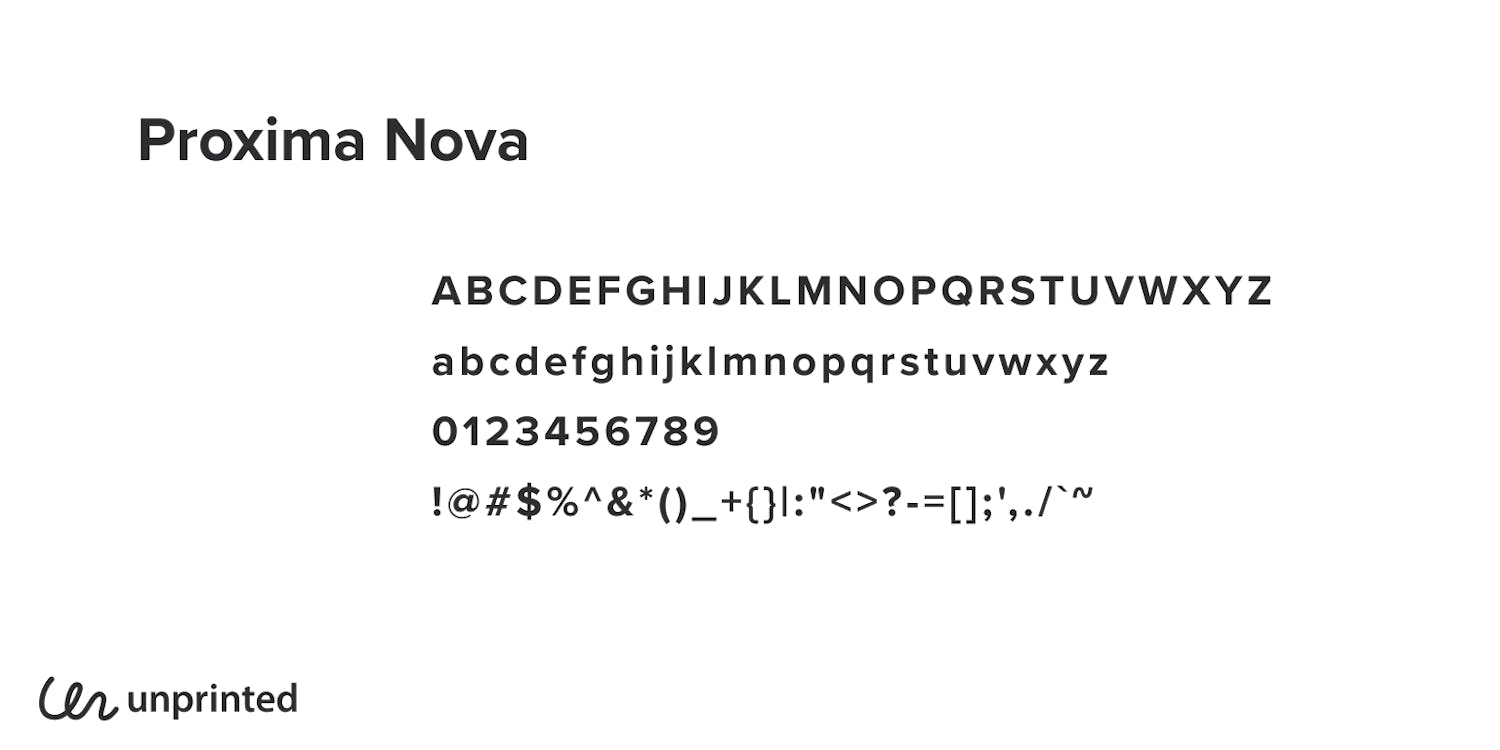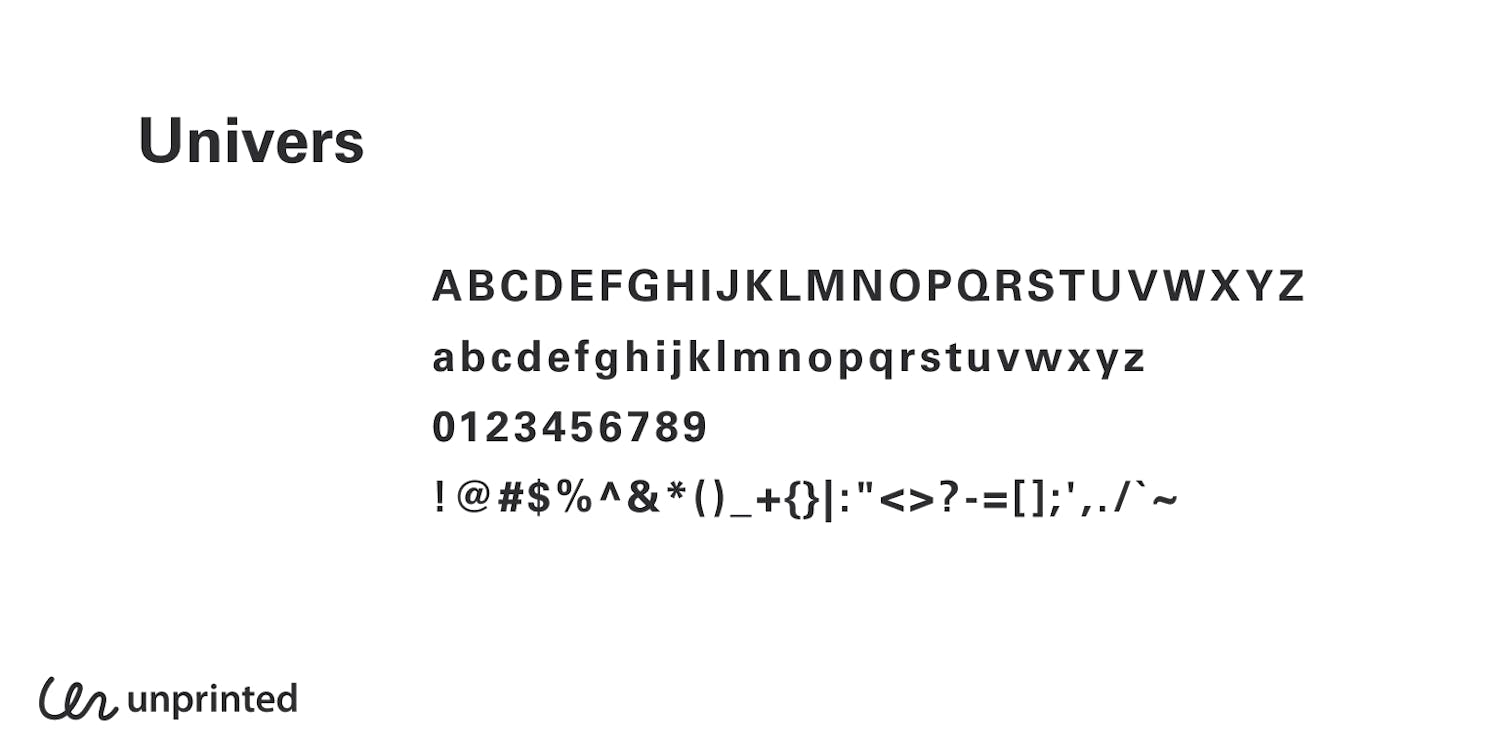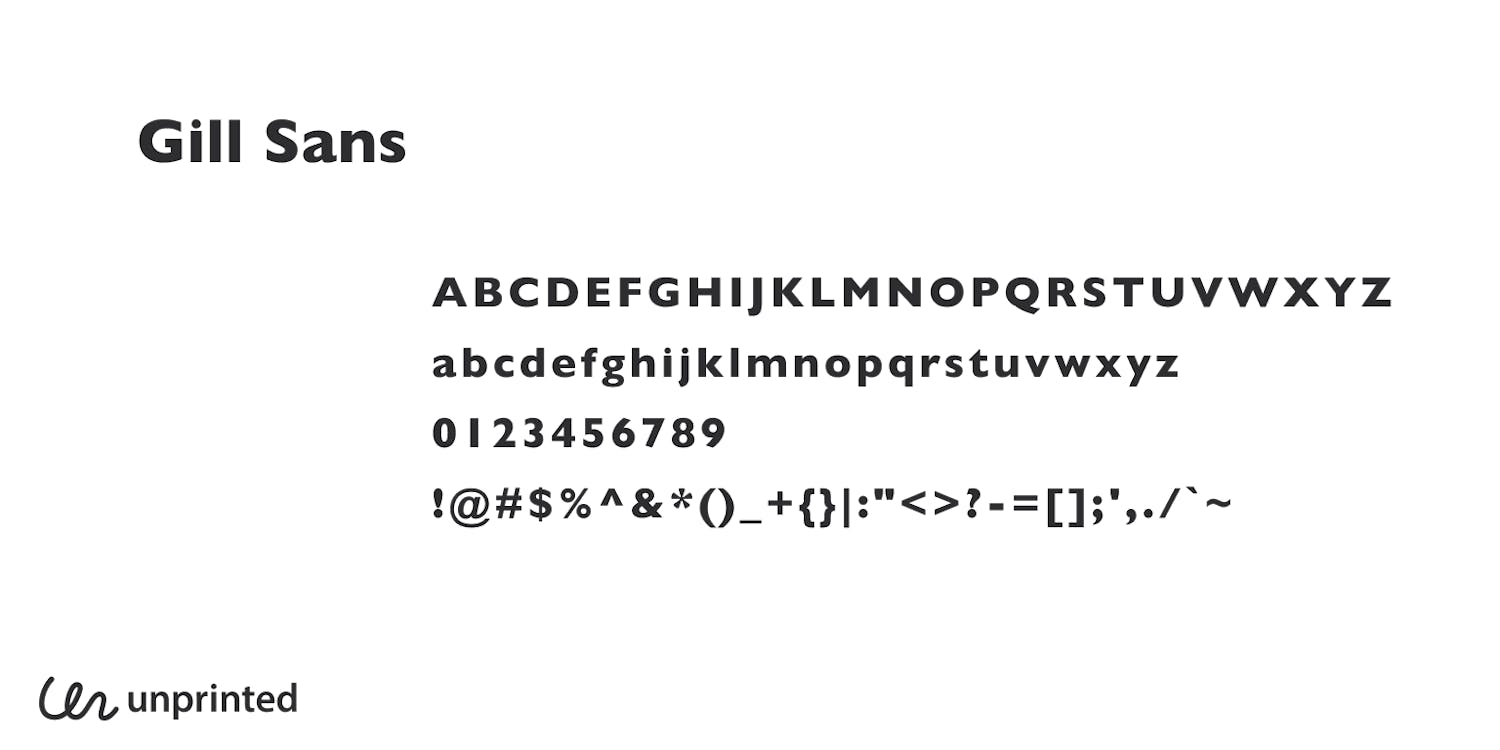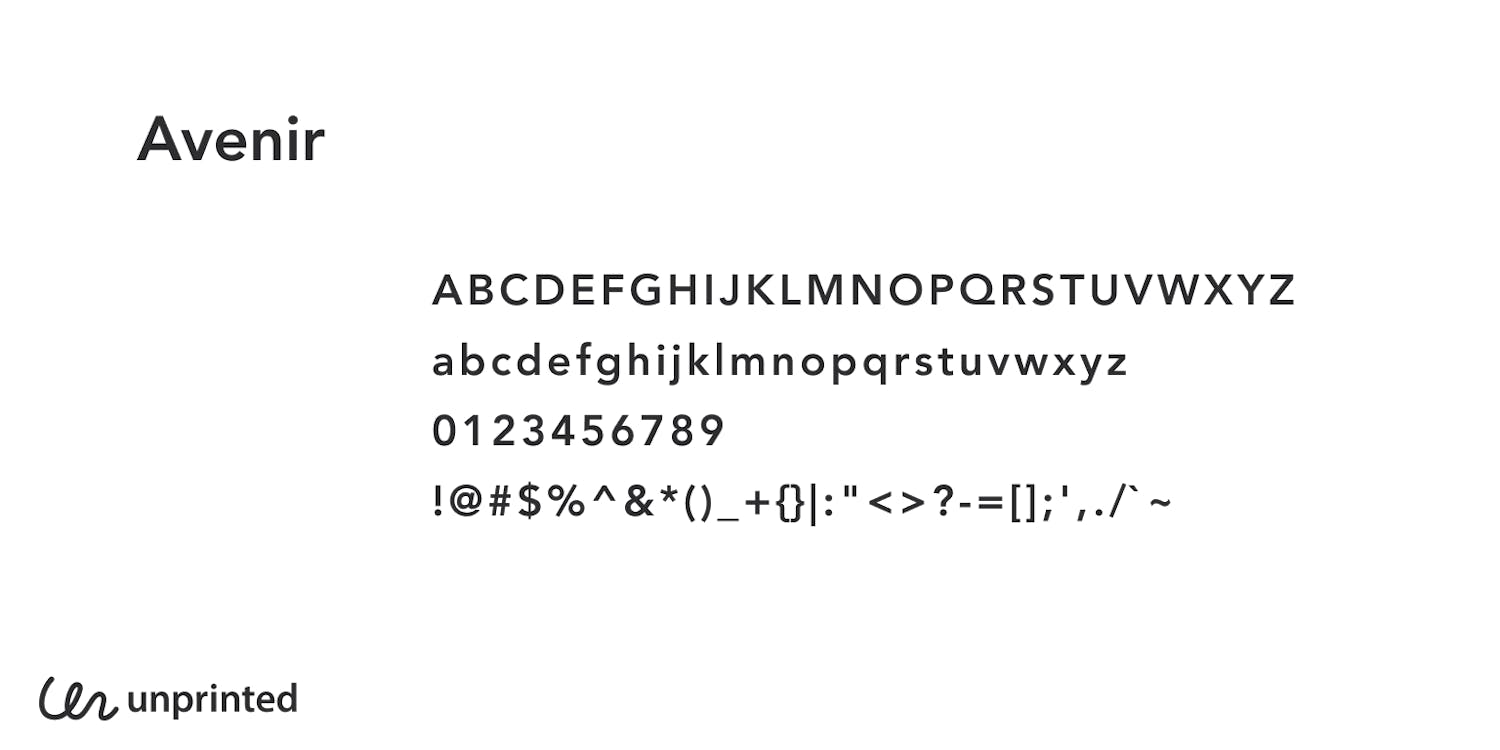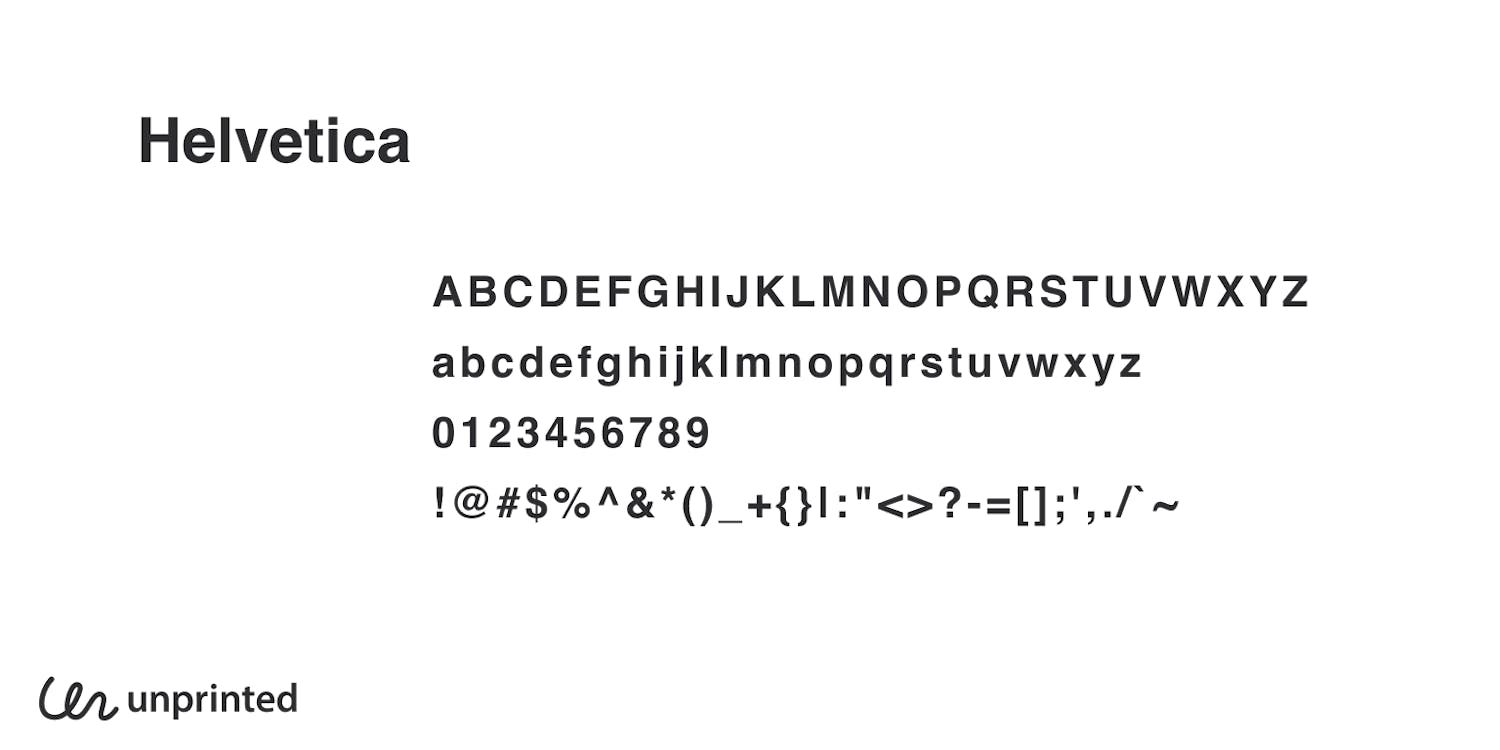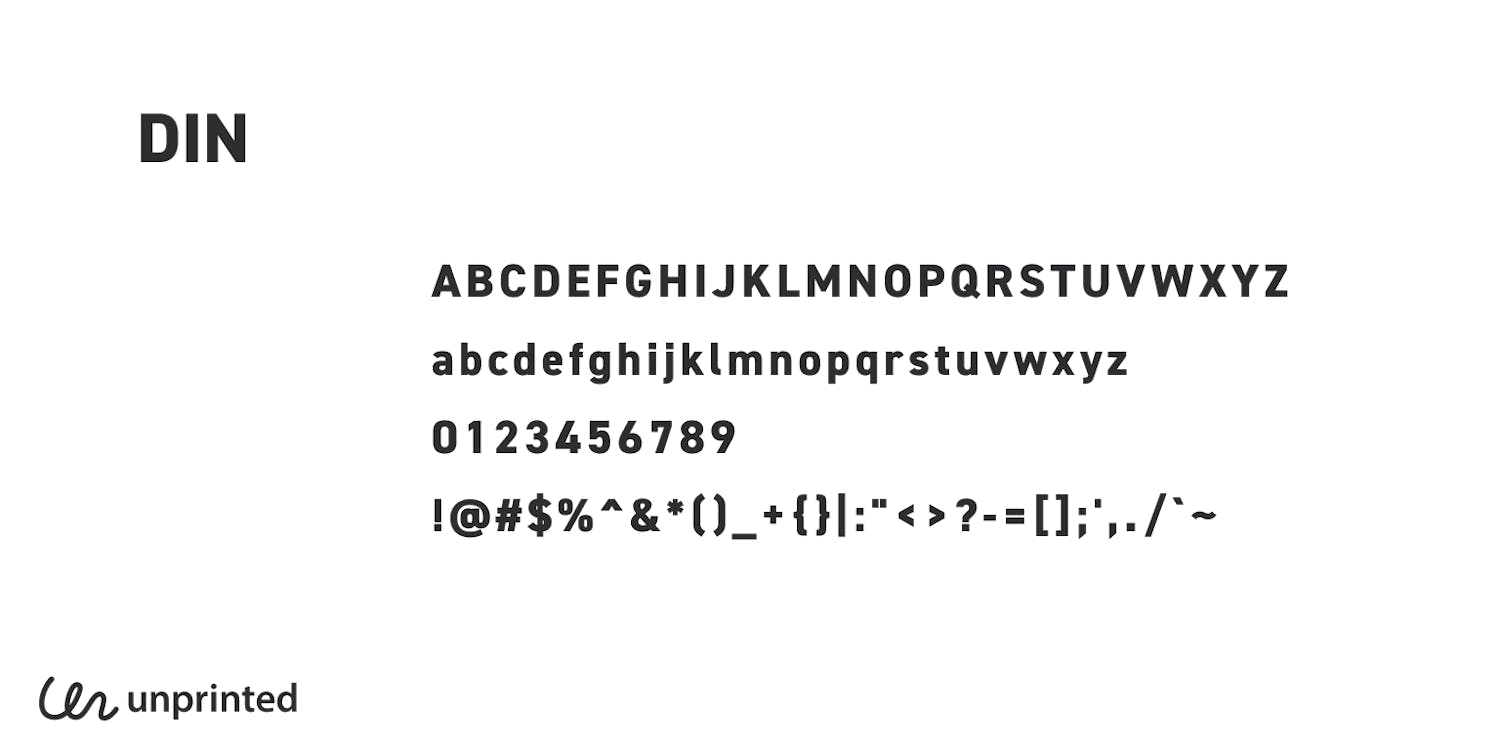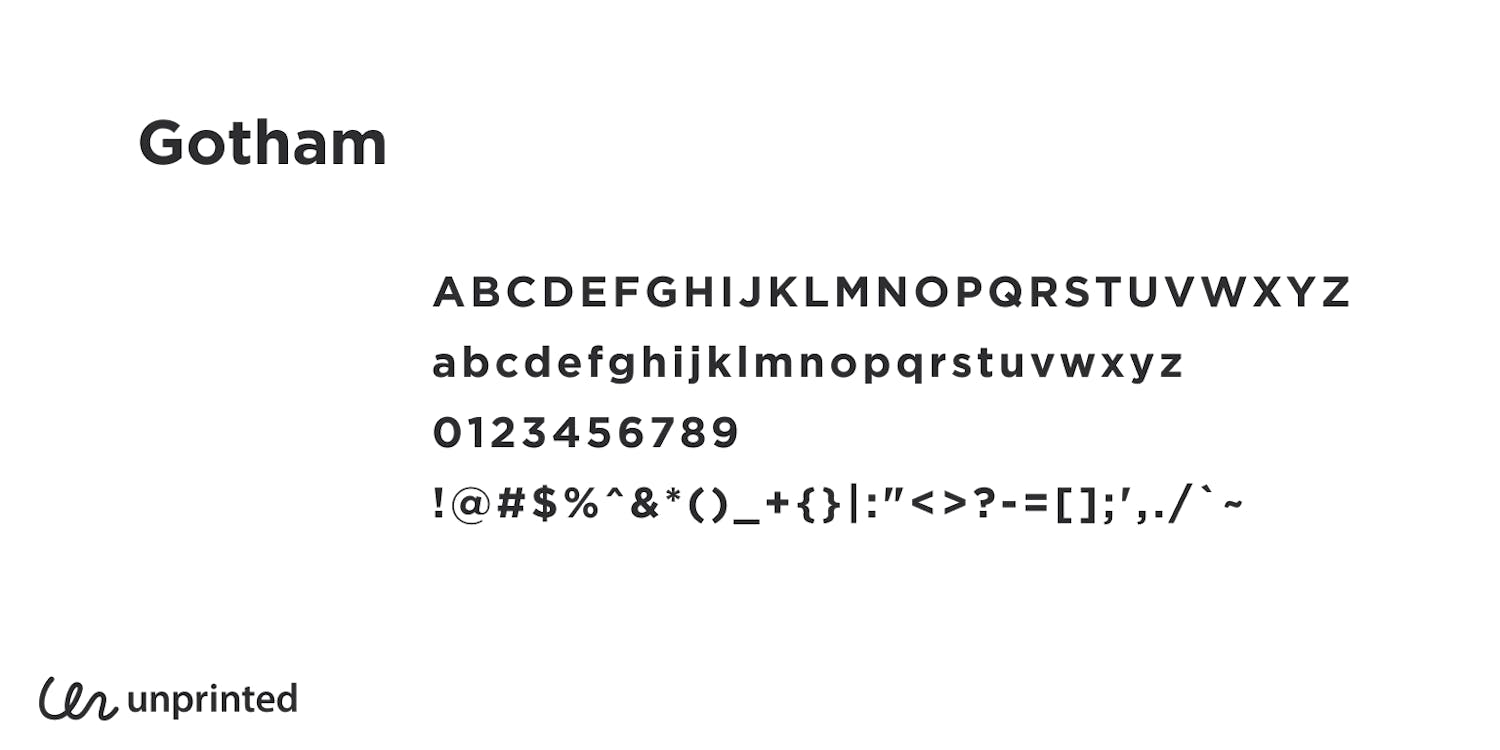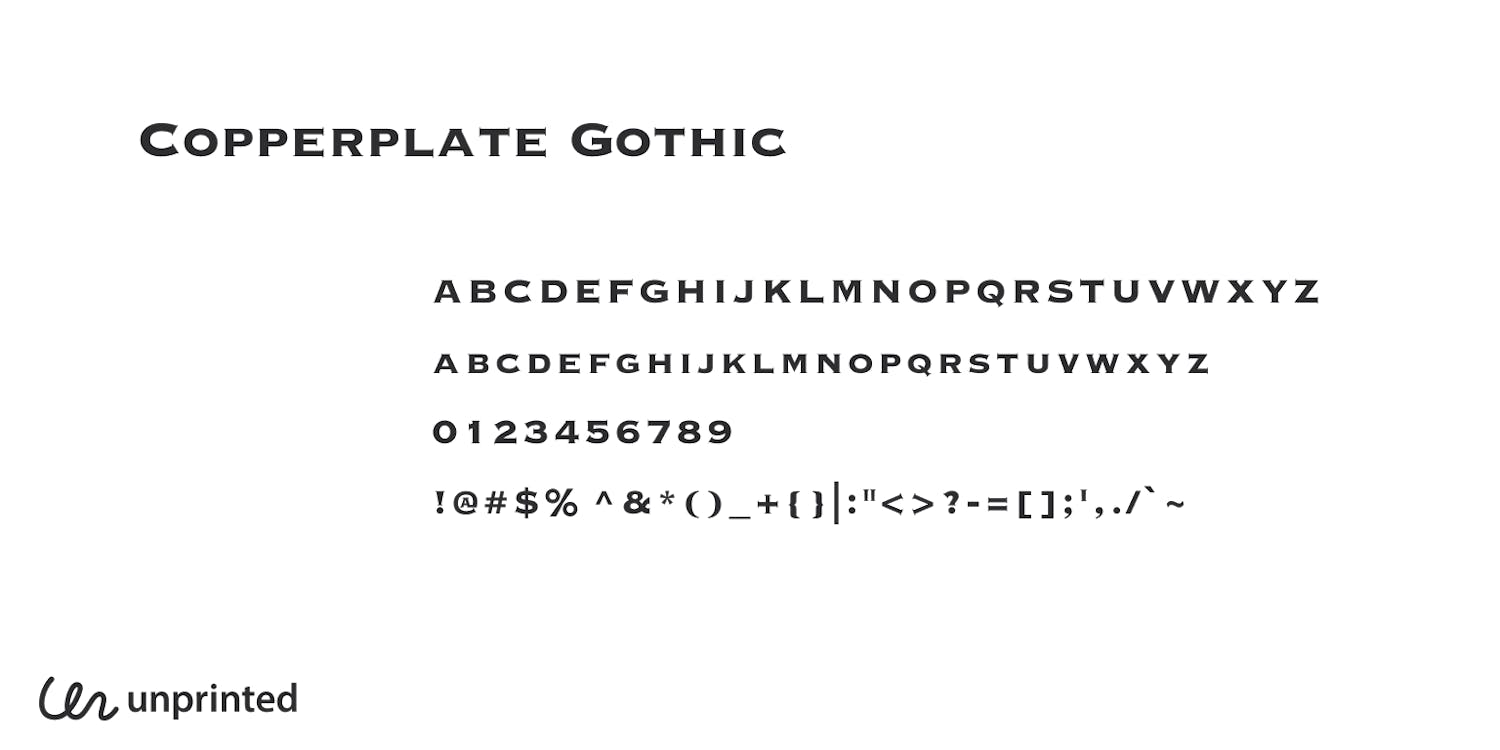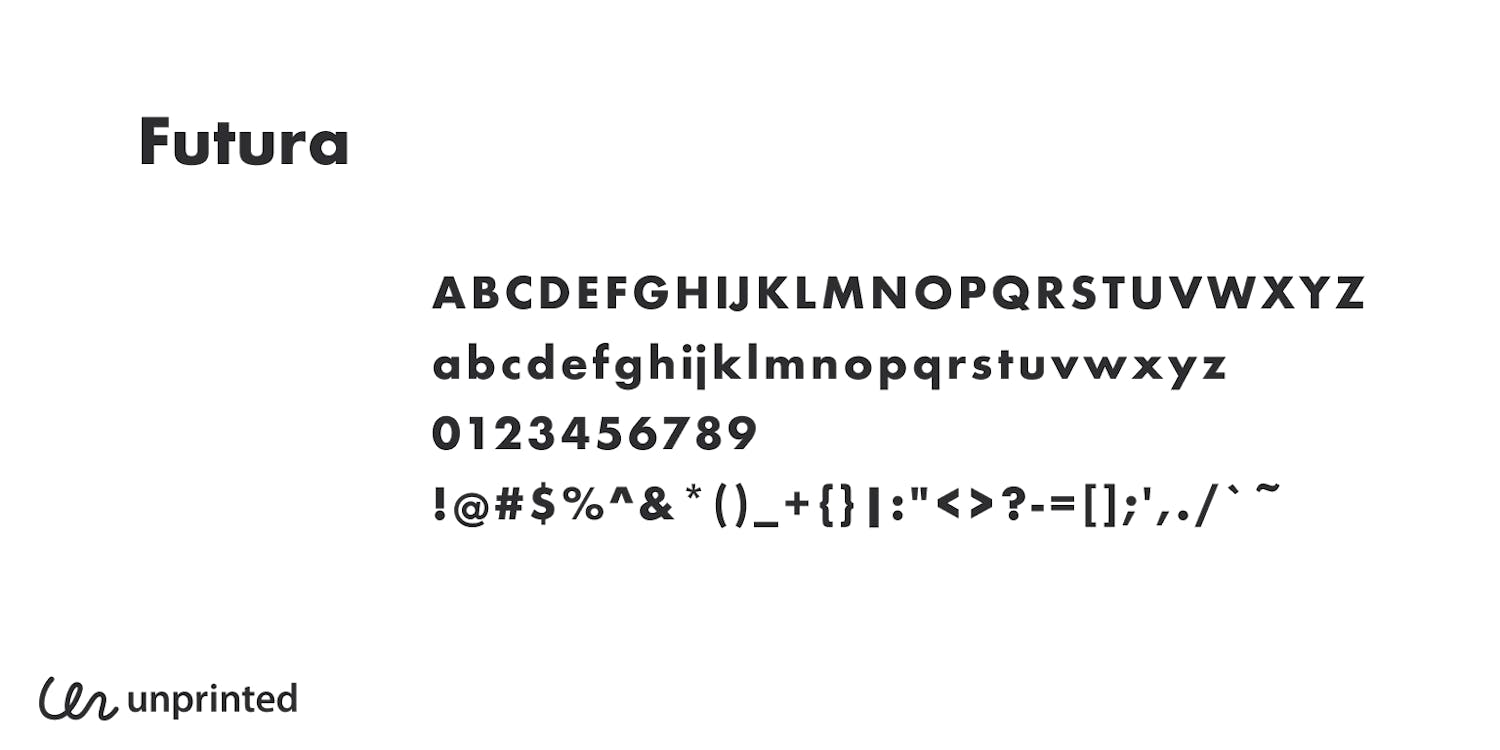
ロゴのデザインに最適な定番13フォントを事例とともに紹介!
ロゴデザインにおすすめの定番13フォントを紹介
ロゴデザインにおすすめの定番13フォント
既存のフォントをもとにロゴタイプを作成しようと思った時にまず迷うのが、どのフォントを使えば良いのかという問題ですよね。フォントは大変多くの種類があるため、どれを選べば良いのか途方に暮れてしまうかもしれません。しかし、実は世の中に存在するロゴタイプの多くはいくつかの定番フォントをもとに作られているケースがとても多いのです。つまり、ロゴデザインに使用するフォントを選択する第一歩として、まずはこれらの定番フォントの中からイメージに近いものを選択し、それをもとにデザインしていくと良いでしょう。
紹介する書体は登場した年代順に並べ、それぞれの書体の解説ではその書体が与えるイメージやロゴとしてよく使われる業界を紹介しているので、作成したいロゴのブランドイメージに照らし合わせて検討してみてください。
1. Didot(ディド) / Bodoni(ボドニ)
Didot(ディド) / Bodoni(ボドニ)
18世紀に生まれたDidotとBodoniは、どちらもファッション業界のロゴでよく使用される書体です。Didotはフランスで、Bodoniはイタリアで生まれ、どちらも細く繊細なデザインが特徴。Didotは、VOGUE, Harper’s Bazaar, Giorgio Armani, Zaraなど、Bodoniは、ELLEなどで使用されています。BodoniはDidotより広いウェイトを揃えていることも特徴です。どちらの書体もファッション業界など、高級感やエレガントな雰囲気を表現したいロゴによく使用されます。
2. Copperplate Gothic(カッパープレートゴシック)
Copperplate Gothic(カッパープレートゴシック)
Copperplate Gothicは、1901年にフレデリック・ガウディによってアメリカで制作されたセリフ体です。力強く洗練されたデザインが特徴です。Copperplateとは銅版を意味する英語で、Copperplate Gothicは銅版印刷時代の書体をベースに作られています。それぞれの文字が正方形に収まるような形をしていることが特徴。Copperplate Gothicは、DEAN & DELUCA, MOLESKINEなどの企業のロゴに採用されています。タイトルでの使用を想定してデザインされているため、小文字が存在しない(小文字と大文字のデザインが同じ)ことも特徴で、法律事務所やレストランなど、伝統や高級感を表現したい場面でも多く利用されています。
3. Futura(フーツラ)
Futura(フーツラ)
Futuraは1923年にバウハウスで非常勤講師を務めたドイツのタイポグラファー、パウル・レナーによって設計されました。このジオメトリック・サンセリフの書体は、OMEGA, LOUIS VUITTON, Volkswagenなどの企業のロゴで使用されています。幾何学的な形状とモダンなデザインは、高級感のあるイメージを与えたいロゴによく使用されます。書体名のFuturaは、「未来」を意味するラテン語に由来。
4. Gill Sans(ギル・サンズ)
Gill Sans(ギル・サンズ)
1926年に英国のエリック・ギルによって設計されたGill Sansは、英国のモダニズム運動の一部として開発され、ヘルベチカよりも先に登場した書体ではあるものの「イギリスのヘルベチカ」とも言われています。BBCやBritish Railwaysなどの英国の企業や政府機関でよく使用されるこの書体は、クラシカルかつプロフェッショナルな外観が特徴です。ヒューマニスト・サンセリフに属し、人間味のある特性と独特の文字形状は、時代を超えたエレガントさを提供します。Gill Sansは、BBC, MARGARET HOWELL, Philipsなどの有名企業のロゴに採用されています。
5. DIN(ディン)
DIN(ディン)
DINは1930年代にドイツで工業用に作られた書体です。書体名も「ドイツ工業規格(Deutsches Institut für Normung)」に由来し、ドイツの道路標識や公共情報表示で広く利用されています。その機能主義的なデザインと清潔な線は、モダンなデザインの要素として多くの企業に採用されています。DINは、ドイツの公的機関のロゴに採用されているほか、日本ではユニクロのロゴとして有名ですね。
6. Helvetica(ヘルベチカ)
Helvetica(ヘルベチカ)
Helveticaは、1957年にスイスのタイポグラファーのマックス・ミーディンガーとエドゥアルト・ホフマンによって設計され、そのクリーンで読みやすい特性から、多くの企業ロゴで使用されています。Helveticaは、サンセリフの代表と言っても良いような時代を超えた普遍的なデザインで、Panasonic, アメリカン航空, エビアン, 無印良品, フランフラン, FENDI, BMW, ノースフェイス, American Apparelなど、非常に多くの業態の企業のロゴで使用されています。主張が強すぎず、中立的な印象を与えたい場合などに最適です。書体名のHelveticaは、「スイスの」を意味するラテン語に由来。「ネオグロテスク」というサンセリフのカテゴリーに属し、モダンデザインの影響を受けたデザイナーたちに長年愛されてきました。
7. Univers(ユニバース)
Univers(ユニバース)
Universは、1957年にアドリアン・フルティガーによって設計されました。この書体は、広範なウェイトと幅のシステムを特徴とし、その中立的な設計が多くのデザイナーに支持されています。UniversはEbay, Fedex, Palantir, UNICEFなどのロゴで使用されており、そのクリアなラインと柔軟性から、コーポレートアイデンティティやブランディングに非常に適しています。Helveticaと同年に誕生し、見た目にも一見似ているこの2つの書体ですが、Helveticaは19世紀のサン・セリフ体を改刻し作られたのに対し、Universは15世紀のローマン体をベースにしています。そのため、Helveticaと比べ少し丸みのあるデザインが特徴で、Helveticaよりも幅広いウェイトを揃えているため、より多様なデザインに利用しやすいです。
8. Optima(オプティマ)
Optima(オプティマ)
Optimaは、1958年にヘルマン・ツァップによってデザインされたドイツのヒューマニスト・サンセリフ書体です。Optimaは古代のローマ碑文に影響を受けており、サンセリフ体でありながら、裾が広がるデザインでエレガントな印象を与えます。Aston Martin, Jaguar, Aesopなどで使用されています。